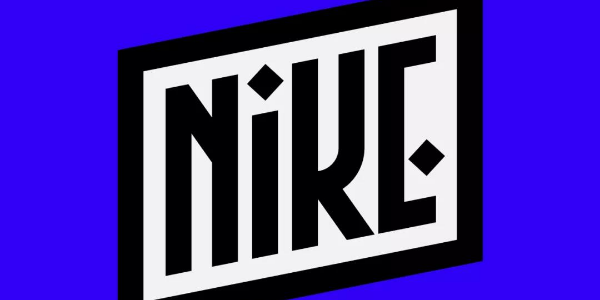
2019爱沙尼亚设计大奖公布,8大类别一篇全览
2019爱沙尼亚设计大奖共有88件获奖作品脱颖而出,其中有23个金奖、24个银奖和27个铜奖。该奖项意在评选出得到爱沙尼亚设计界广泛认可的优秀作品,这也将是爱沙尼亚本土设计作品的展示平台,更是多国设计师交流和学习的平台。
本文将展示字体版式设计、插画、书籍设计、印刷品设计、日常化包装设计、独家定制包装设计、品牌形象、环境视觉设计,共计8大类别的金、银、铜奖作品。
字体版式设计
金奖
X档案 (The X-Files)
客户:爱沙尼亚艺术博物馆
“ X档案”是一个展览,试图深入研究1990年代爱沙尼亚当代艺术界中更神秘的地方。展览标题以拉丁字母和装饰符号组合设计;入口的墙壁露出了象形文字图案,这是一篇有趣的加密文档,供能够解密的人阅读。
银奖
Balticbest 2018
Balticbest是一个精品节,2018年以来,波罗的海各州均开放参加,因此需要一个新的品牌视觉和广告界交流。为了保持焦点清晰,视觉语言没有任何多余的装饰,字体构成了视觉的基础。
铜奖
Eisma Sailing 品牌视觉
由FAN设计师/合作伙伴MathiasVäärsi创建的字体Paulie被用于Eisma SailingMTÜ视觉标识。当然,也对Paulie进行了部分修改以满足需要,因此它也有了一个新名字:Sailor Paulie Bold。
金奖
Pirita 冲浪节海报
作者:Rainer Kasekivi
这是一套充满趣味的超现实漫画,虽说是宣传海报,但是设计师在尽力降低插画的广告意味,而是专注于创造好奇心。
银奖
Värske Rõhk nr 57
作者:LiisiGrünberg
第57期Värske Rõhu杂志由插画师 LiisiGrünberg 操刀,不仅提供杂志主题封面和内页配图,也创作一些诗歌和短篇小说的配图。
铜奖
Folk TIKS
这是为爱沙尼亚歌舞节后的狂欢绘制的海报,主题是“向人类致敬”。
书籍设计
金奖
Pallas 100
设计师:Valter Jakovski
银奖
Kahe heli vahel
图画小说《两个声音之间》讲述了阿尔沃·帕特(ArvoPärt)从童年到1980年移居爱沙尼亚的音乐故事。为了展示作曲家的音乐和内心世界,作者创建了特定的图形元素,形式、线条和颜色用于阐明内容。
铜奖
Kunst on moos elu saiakäärul.
Artishoki artiklikogumik 2006-2018
当设计师同时也是作家和编辑时,就会诞生这样一件作品。这本书的非常规结构探索了内容层次的可能性,书中的论文按时间顺序排列,而目录则提供了完全不同的主题阅读地图。
印刷品设计
金奖
TDH品牌手册
TDH品牌手册提供了爱沙尼亚设计师品牌的全面概述,其主要目的是帮助设计师进入新的出口市场。惊喜的是,还包括了特别选择的新爱沙尼亚音乐CD。
银奖
Pallas 100 展览海报
作者:Valter Jakovski
铜奖
Linnafestival UIT 2019
作者:Martin Rästa
城市庆典UIT是一个针对特定地点的艺术节,旨在从新的角度探索塔尔图的城市空间。系列海报由三个海报“ U”、“ I”、“ T”组成一个整体,但每个海报也各自起作用。海报非常注重版式的平衡,对比鲜明的配色方案也是整个视觉不可分割的一部分。
包装设计
<日常化包装>
金奖
Say Yes to Can
包装从玻璃瓶改为了铝制金属罐,因为它100%可回收,这意味着罐子的每个部分都会再次使用,它也比玻璃轻。例如,这可以降低运输成本,因为我们可以在同一批货物中运输更多啤酒。紫外线和氧气会破坏啤酒的味道,由于铝制金属罐是完全不透气的,因此它们不会引起气味或味道的变化。
银奖
JOIK Organic 包装设计
铜奖
Kape x Martinex
以人名命名的厨房设备的包装和品牌标识,轻快有趣,可以在市场上同类产品的包装中脱颖而出。
包装设计
<独家定制包装>
金奖
Liviko CXX peenviin
CXX是真正的手工伏特加酒,是120年爱沙尼亚丰富的蒸馏传统的结晶,限量发行。利沃科(Liviko)酿酒厂采用大量的富铜设计,并在包装上采用手绘插图。
银奖
Moco袜子包装
铜奖
Junimperium
通过将经典的“药瓶”包装、经典的标签与现代设计相结合,我们创造了一种在饮料架上脱颖而出的组合。
品牌形象
金奖
Wasa 度假村
银奖
Sveta baar & vintage
品牌视觉以霓虹灯管的显示和洒脱的书法字体为主,彰显了品牌想要传达的自由随性的生活态度。
铜奖
杜松子酒品牌Junimperium
环境视觉
金奖
Suure-Jaani 健康中心
银奖
超级空中公园
铜奖
国防科学院